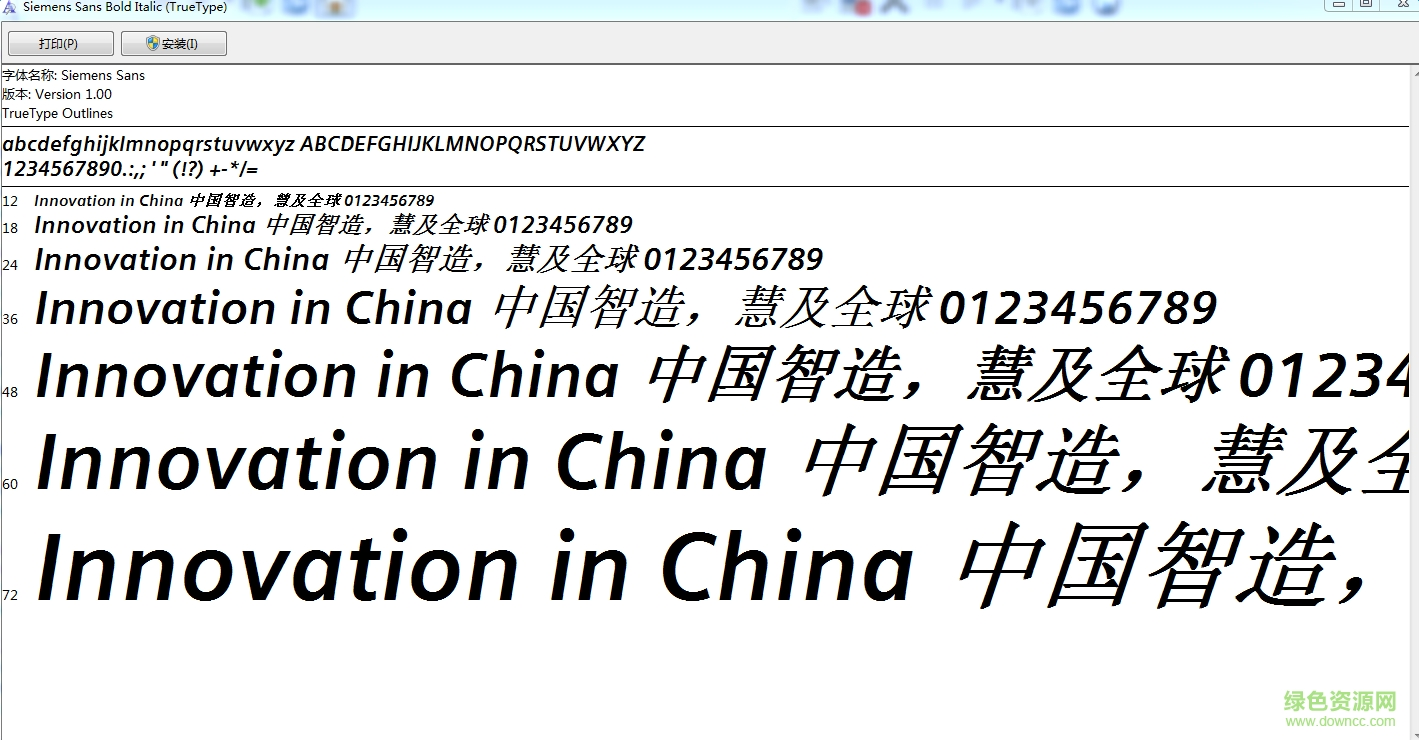
siemens sans字體
siemens sans字體是一款英文字體,該字體線條較粗,結(jié)體嚴(yán)整,效果出色,支持中英文輸入,感興趣的朋友歡迎在綠色資源網(wǎng)下載!
字體介紹
siemens sans字體是一款用于美工設(shè)計(jì)方面的英文字體,該字體樸茂工穩(wěn)、靈秀清麗、看上去十分美觀,整體效果非常統(tǒng)一,且字庫完整,可以廣泛應(yīng)用于名片設(shè)計(jì)、新聞媒體、宣傳海報(bào)、ppt、影視制作以及任何使用文字的領(lǐng)域,有需要的朋友可以免費(fèi)下載收藏。